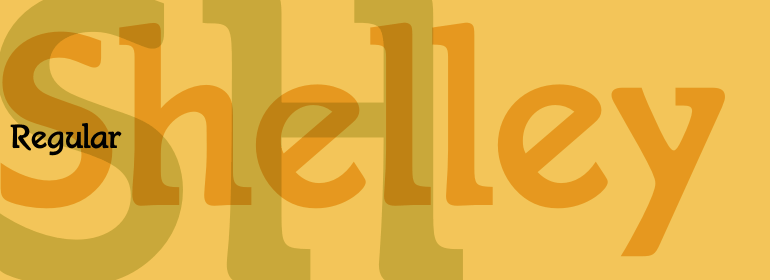
Shelley®
Shelley®,这款字体结构工整、笔画清晰,兼顾美观与易读性,适用于标题、正文、海报、包装、LOGO 等多种场景。字形优雅稳定,风格百搭耐看,适配日常排版与创意设计,让文字呈现更舒适、更具质感。Shelley®一笔一画,皆是细节,以均衡的比例、流畅的线条打造舒适视觉体验,字形端正大气,风格简约现代。无论是商业设计、品牌宣传还是日常排版,都能轻松驾驭,让文字更有格调与力量。Shelley®字体下载。